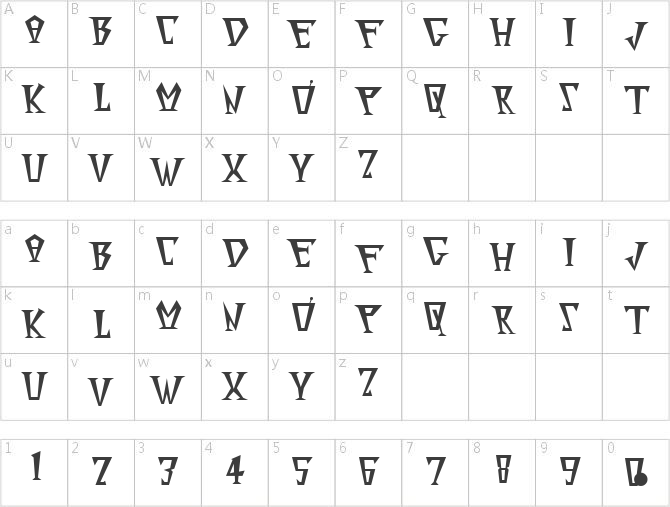
Surfin'ta Mars 詳情頁(yè)
Surfin'ta Mars字體字庫(kù)是一款讓人賞心悅目、百看不厭的英文字體,適合各類(lèi)廣告和產(chǎn)品包裝設(shè)計(jì)應(yīng)用,字體大小0.01MB,格式為ttf字體,上傳用戶(hù)是23KUN,作者/版權(quán)方為未知